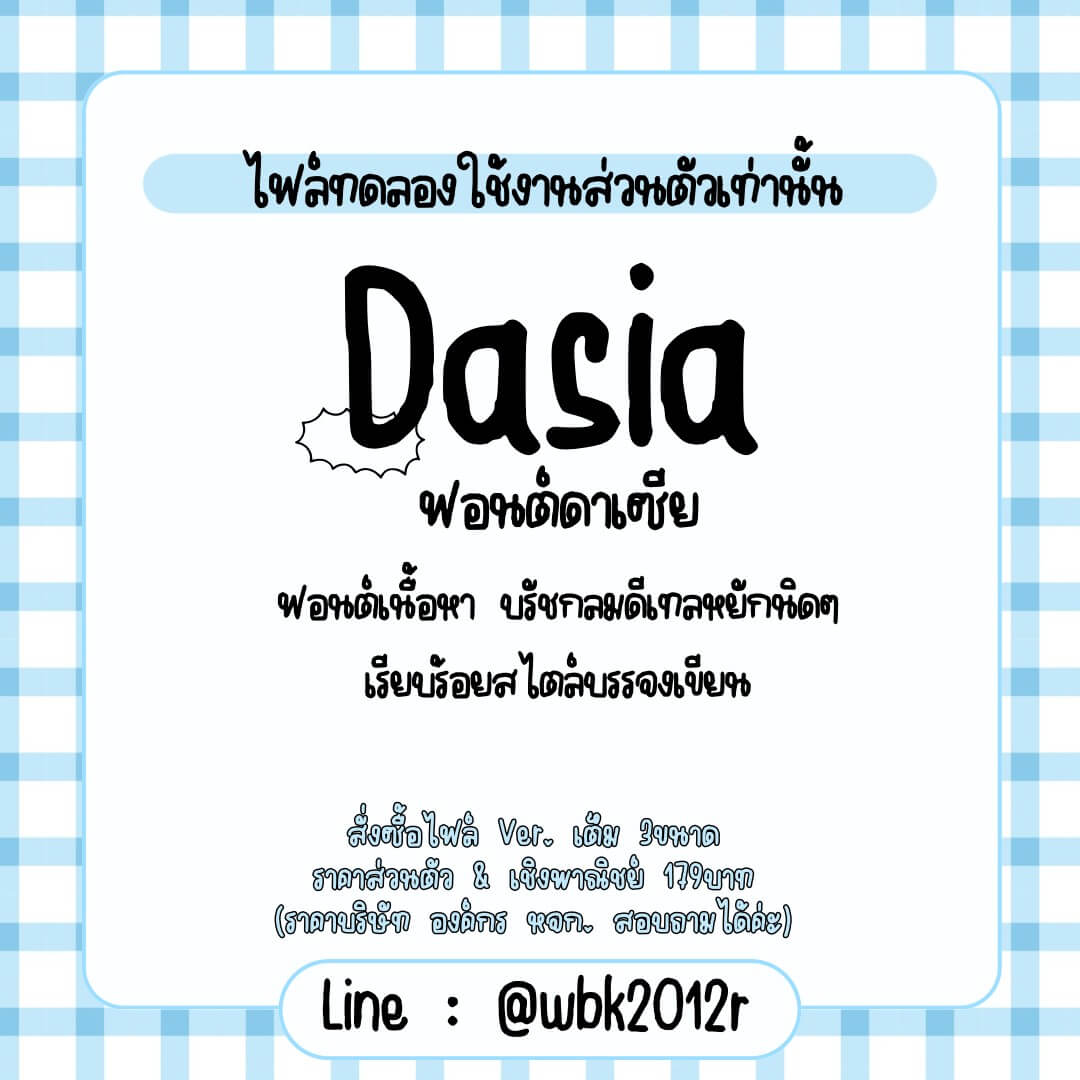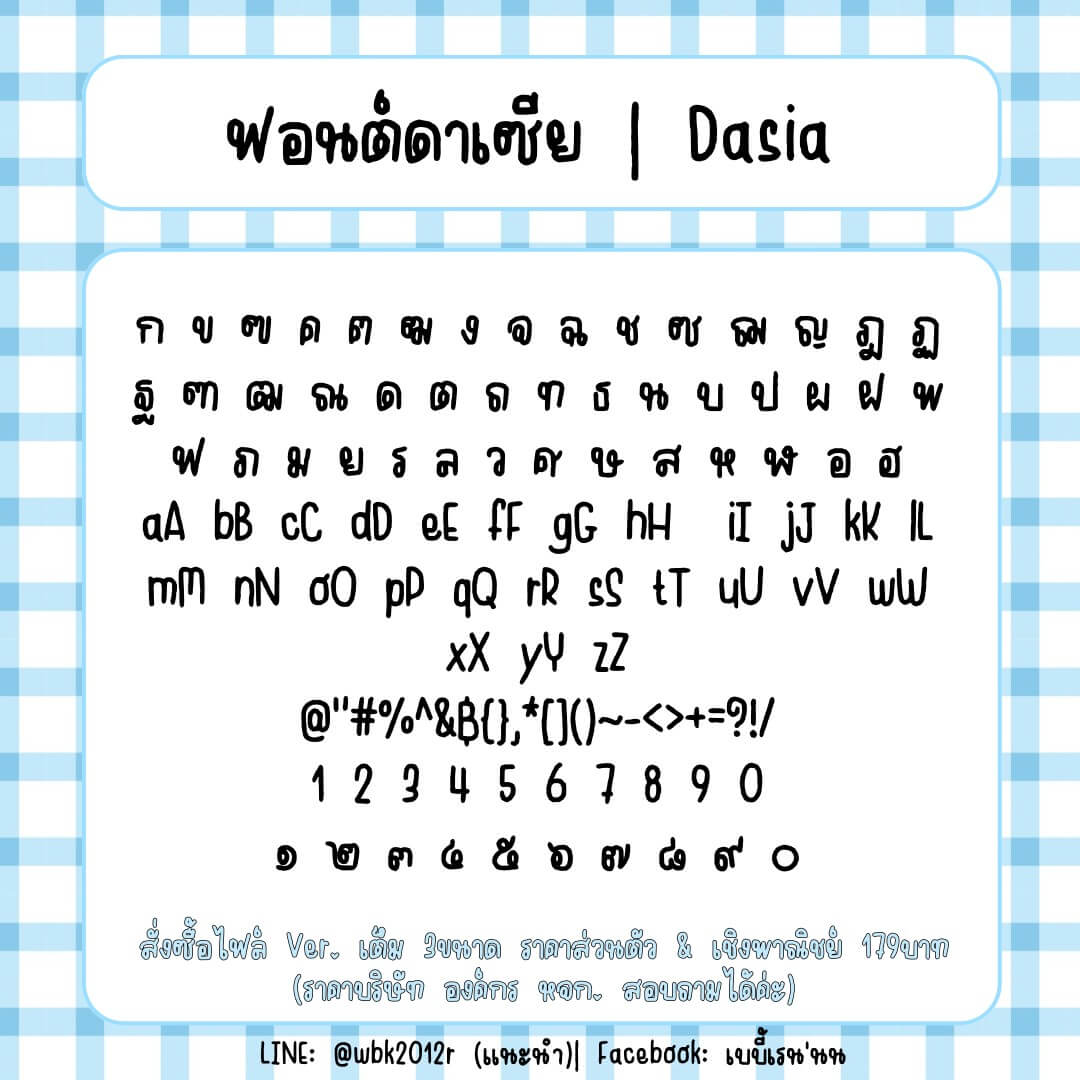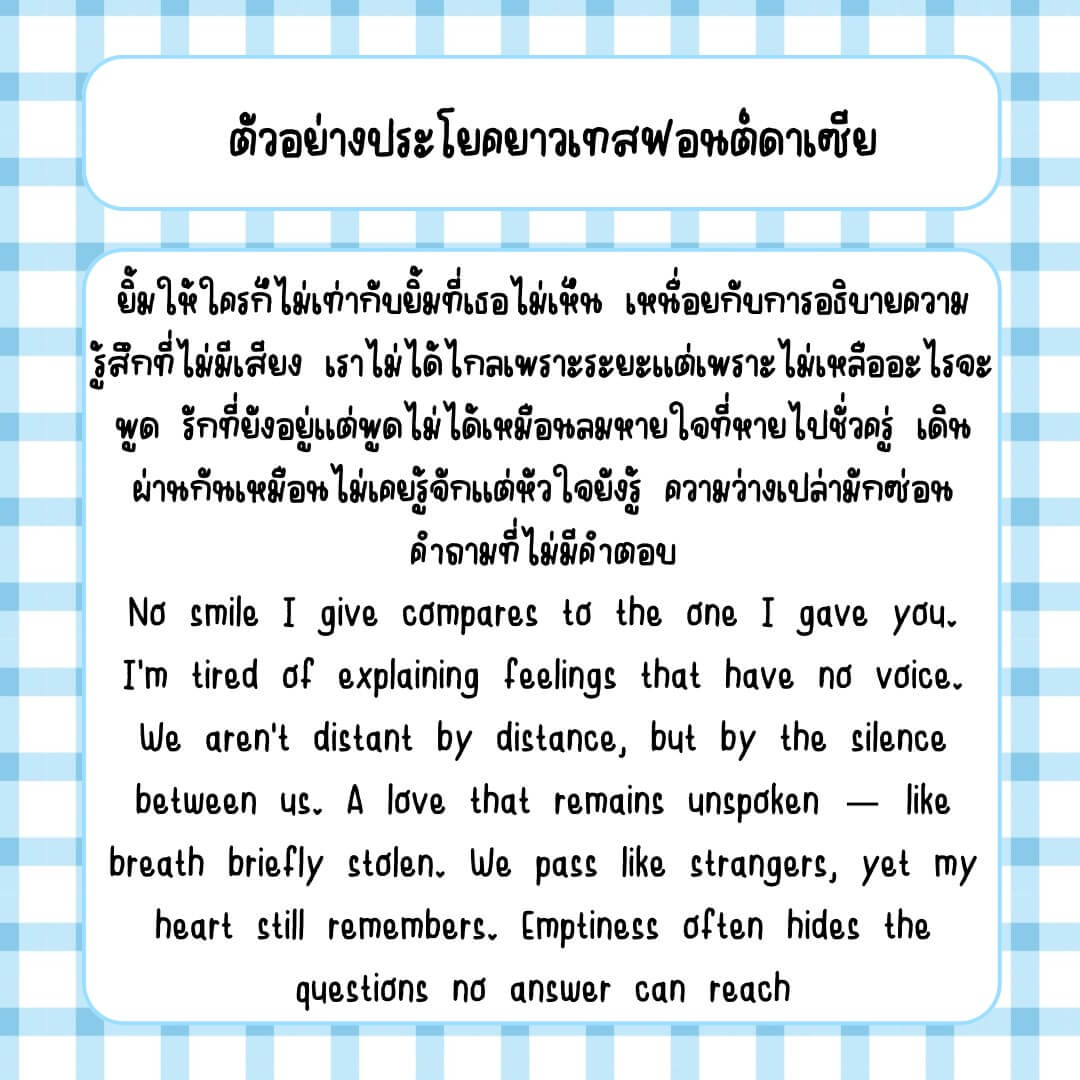
PRHDasia / ดาเซียฟอนต์ – ฟอนต์เนื้อหา บรัชกลมดีเทลหยักนิดๆ เรียบร้อยสไตล์บรรจงเขียน
- ฟอนต์มีขนาดไม่เท่ากัน / ไม่มีเลข/วรรณยุกต์ / อักษรโปร่งบางตัว
ดาเซีย (PRHDasia)